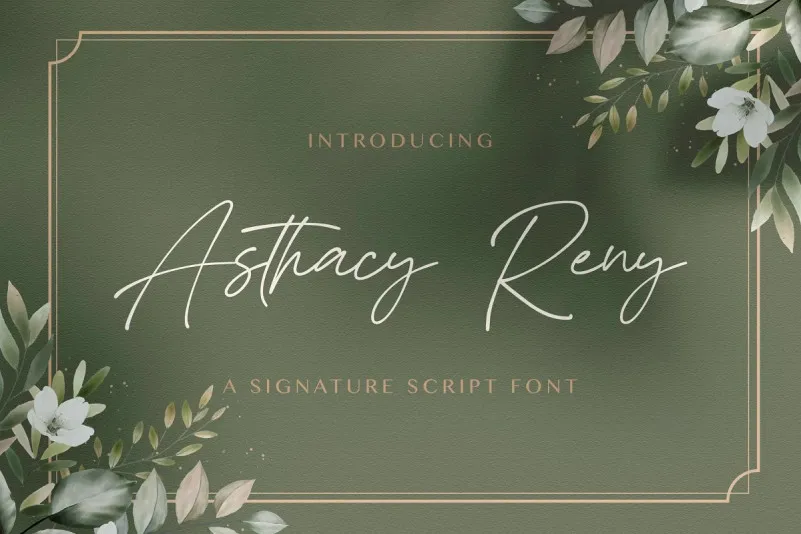
A Asthacy Reny Font é uma elegante e fina fonte script que se destaca pela sua delicadeza e estilo sofisticado. Manufacturada pela StringLabs, esta fonte apresenta caracteres bonitos e bem equilibrados, o que a torna perfeita para uma vasta variedade de projetos criativos. Composta por linhas finas e traços delicados, essa fonte se adapta perfeitamente a diversos estilos gráficos, sendo uma escolha ideal para designers em busca de um estilo único e sofisticado. Adicione a Asthacy Reny Font a seus projetos mais audaciosos e verá como ela os torna vivos e impressionantes.